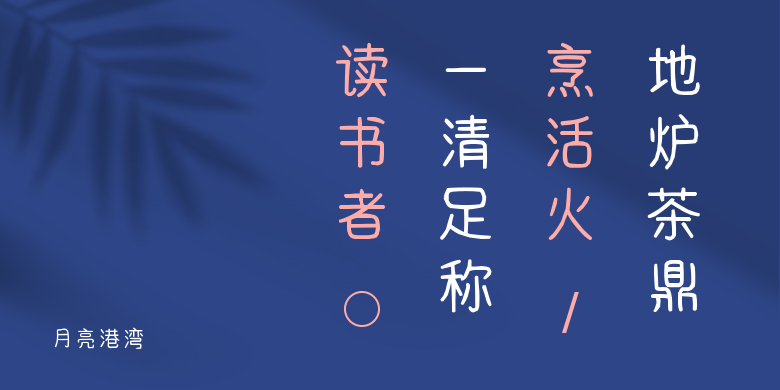
月亮港湾
月亮港湾,这款字体结构工整、笔画清晰,兼顾美观与易读性,适用于标题、正文、海报、包装、LOGO 等多种场景。字形优雅稳定,风格百搭耐看,适配日常排版与创意设计,让文字呈现更舒适、更具质感。月亮港湾一笔一画,皆是细节,以均衡的比例、流畅的线条打造舒适视觉体验,字形端正大气,风格简约现代。无论是商业设计、品牌宣传还是日常排版,都能轻松驾驭,让文字更有格调与力量。月亮港湾字体下载。